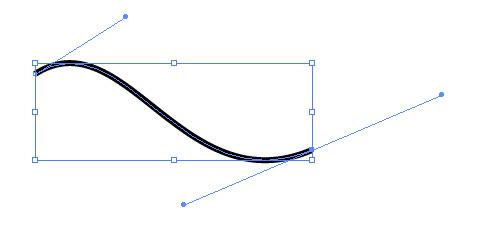
PostScript vs. TrueType
Wolfgang Becker, mein Prof für Typo in Stuttgart, hat uns diesen Unterschied deutlich gemacht. Ich kann mich definitiv daran erinnern bzw. habe es in meinem Skript niedergeschrieben, dass TT mit »quadratischen Kurven« arbeitet, PS hingegen mit »Polynomen dritten Grades«.
Das ermöglicht in ein und derselben Kurve einen Gegenschwung nur mittels der Anfasser:
Spielt die Schönheit der mathematischen Formel eine Rolle in einer Welt, in der sämtliche Ausgabegeräte nicht fähig sind, mit Vektoren umzugehen, sondern alles in Pixeln/Punkten darstellen?
Kubische oder Quadratische Kurven (beides sind übrigens Bezier-Kurven, nur unterschiedlicher Ordnung) und deren Effizienz:
Das relativiert sich ein wenig, wenn man  berücksichtigt, dass die quadratischen Kurven nur einem Anfasser-"Hebel" für jeweils zwei Kurven-Punkte braucht, während bei kubischen Kurven zwei getrennte Tangenten im Spiel sind.
Oder wie's im Wikipedia-Artikel eh gezeigt wird (Mitte: quadratisch,  rechts: kubisch):
Diese Hilfspunkte müssen aber natürlich genauso gespeichert und verarbeitet werden, d.h. die quadratischen Kurven haben auch wenn sie mehr Punkte brauchen diesbezüglich nicht zwingend einen Nachteil (und ob er signifikant ist, ist nochmal eine andere Frage).
Letztlich ist das für die Qualität einer fertigen Schrift nicht relevant – mit beiden Modellen kann man jede benötigte Kurve beliebig genau annähern – der Schriftgestalter muss sich mit dem Werkzeug halt wohlfühlen und Mühe geben, da spielt dann auch viel Gewohnheit mit rein was einem mehr liegt.
Qualitätsunterschiede entstehen immer nur, wenn man von einem Modell ins andere umrechnet, und diese Umrechnung nicht mit genug Mühe gemacht wird*. Bei der Umwandlung von kubisch nach Quadrat muss am Wendepunkt der Kurve ein neuer Punkt gesetzt werden. Beim Umwandeln in die andere Richtung müssen überflüssige Punkte entweder entfernt werden, oder die Tangenten anders berechnet werden (und man hat dann unnötig viele Punkte in der Kurve). Beides geht mit den richtigen Rechenmodellen und genügend Iterationen beliebig genau. Beim Setzen zusätzlicher Punkte kommt noch hinzu, dass die Positionen auf Ganzzahlen gerundet werden ("müssen"), d.h. ein Punkt kann ggf. nicht genau dort platziert werden wo er hingehört, sondern leicht versetzt – dann passt die Kurve nicht ganz genau. Dem kann mit feineren Gestaltungsrastern, wie sie in Truetype ja möglich sind, entgegengewirkt werden.
Das ist halt "damals" massenweise in schlechter Qualität passiert, als man Postscript-Schriften auch in Truetype verkaufen wollte. Aber ein Schriftgestalter der eine neue Schrift mit quadratischen Kurven zeichnet, ist davon aber nicht betroffen, er arbeitet um sowas genauso intuitiv drum rum wie er es beim zeichnen mit kubischen Kurven tun würde.
Eine Umwandlung findet auch dann statt, wenn der Drucker-RIP nur mit kubischen Kurven rastern kann, weil es "nur" Postscript kann – in so einem Fall müssen quadratische Kurven erst in kubische gewandelt werden, um dann gerastert zu werden. Auch hier können bei einer schlechten Umwandlung Abweichungen auftauchen.  Rastert das RIP aber auch von quadratischen Kurven weg direkt (Truetype-Fonts sind ja jetzt nicht grade neu) oder gibt er sich mathematisch entsprechende Mühe, gibt es auch dieses Problem nicht.
Einen "Meister", der das alles bei einer frisch gezeichneten und nicht x-fach automatisch umgewandelten Schrift in einem Druck "sofort erkennen kann", gibt es vermutlich nicht.
* Exkurs:  auch z.B. eine echte Kreiskurve lässt sich mit keiner Bezierkurve abbilden, auch das sind immer nur Annäherungen, die aber ausreichend genau sind. Dass ein Kreis mit 4 Eckpunkten mit kubischen Bezierkurven abgebildet werden kann ist also nicht korrekt – er kann nur so ausreichend genau angenähert werden, dass darüber niemand mehr nachdenkt, wenn er in Illustrator einen Kreis zeichnet. Genauso sollte es bei Schriften sein ... über mathematische Näherungen nachzudenken ist müßig, wenn das Ergebnis stimmt.
Ja, danke für die Ausführungen, denen ich natürlich gerne zustimme.
Die Iterationen müssen mit einer »hinreichenden Genauigkeit« ausgeführt werden, wie ein Mathematiker es nennen würde, dann kann im RIP das Rasterizing, das Umrechnen der Bildpunkte in die PELs (für Picture ELement des Belichters, |= Pixel) abgebrochen werden. Dann sind ausnahmslos alle benötigten Bildpunkte in der geforderten Auflösung errechnet und es kommt zu keinem irgendwie aus den Eigenartigkeiten der Kurven daher webenden informationsverlusten.
Grundsätzlich bin ich der Meinung, dass man überhaupt keine konvertierten Schriften einsetzen sollte, sondern ausschließlich die unkonvertierten, am besten mit händisch gesetzten Stützpunkten versehenen Originale.
Klar, ich weiß auch noch, wie ich in meinem Studentenzimmer in Stuttgart stand und die frisch aus Berlin von meinem Onkel eingetroffene CorelDRAW! 3.0 CD mit den 300 Bitstream TrueType Schriften in der Hand hielt.
Andererseits ein irgendwie komisches Gefühl: Es war nur wenige Jahre her, dass ich an den Sun-Workstations von Berthold gearbeitet hatte, wo die Schriften allesamt meinem Chef gehörten und ich natürlich zu Hause keine einzige besaß. Wir hatten Schriften im Wert von 250.000 DM.